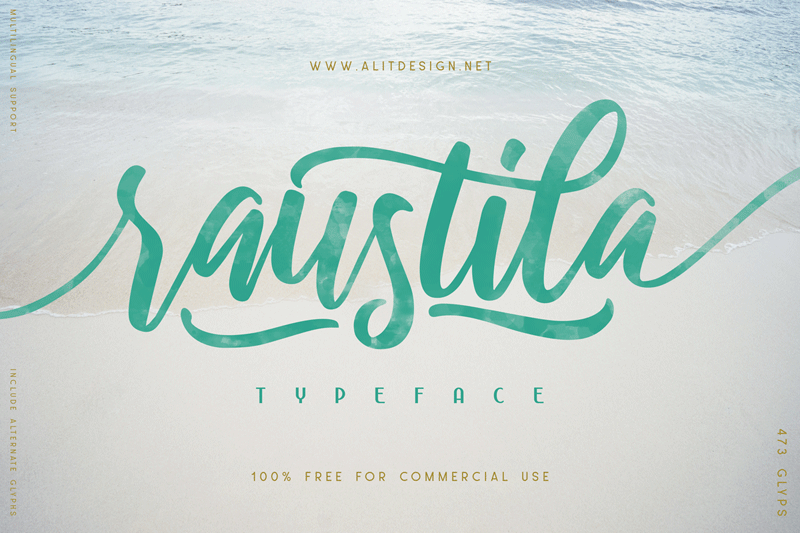
Raustila Typeface – Download Grátis
Introduzimos a Raustila Typeface Script Font! Desenhada pelo alit design, esta fonte oferece uma sensação elegante e única para seus trabalhos de tipografia e identidade visual. Cada letra foi cuidadosamente moldada para tornar seu texto belo. Com o estilo da fonte script, esta opção perfeita para projetos diversos como: citações, cabeçalhos de blog, cartazes, casamentos, marcações, logotipos, moda e vestuário, letras, convites, cartões de aniversário, estaçãoaria. A Raustila Typeface Script é um recurso gráfico perfeito para adicionar uma pitada única ao seu trabalho visual.